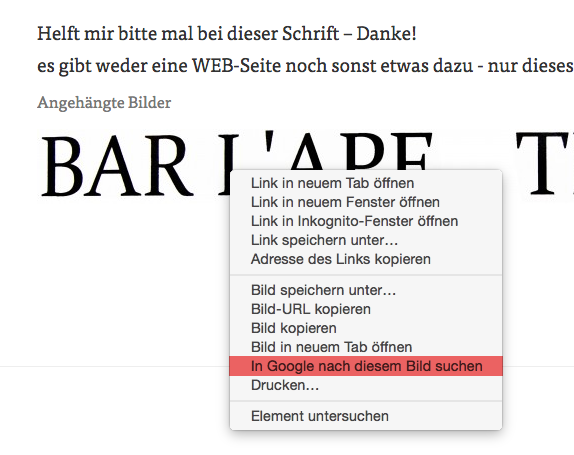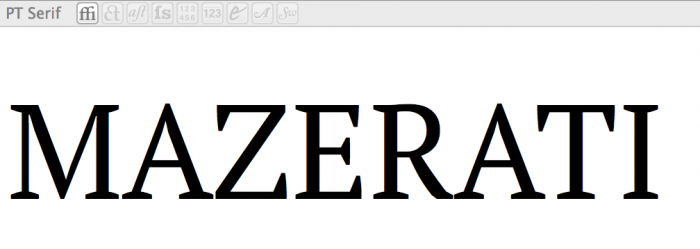
Schriftsuche (Bar L’Ape Tivo)
Die wurde auch hier verendet, ich kenn sie aber leider nicht …
MUSIC ist wohl eine andere Schriftart.
Mazerati verwendet die PT Sans auf der homepage, vielleicht ist das ein Hinweis? Gab’s mal eine Vorgängerversion der PT Serif?
Ich dachte nicht, daß es so schwer ist diese Schrift zu finden, hat sie doch sehr charakteristische Dreieckserifen und -ausläufe.
Von der gesuchten Schrift weiß ich noch, daß der Gesamtentwurf aus der ich die Buchstaben entnommen habe von einer Italienerin stammen könnte. Kann es sein, daß es in Italien eine Schriftschmiede gibt, deren Schriften kaum jemand bekannt sind?